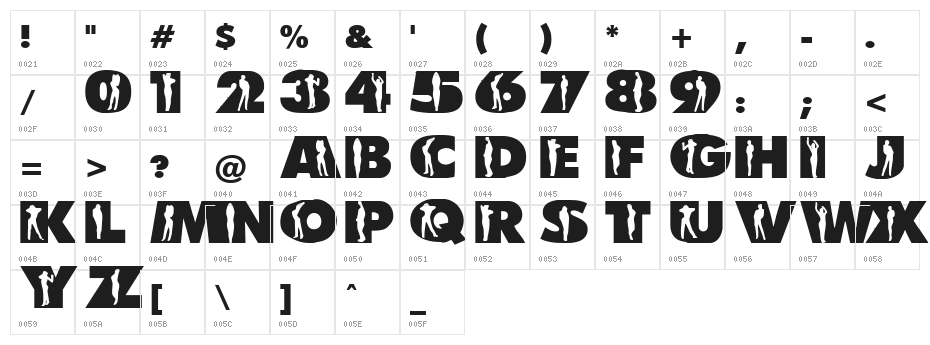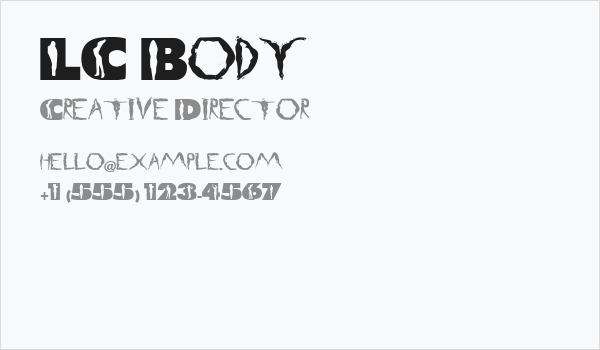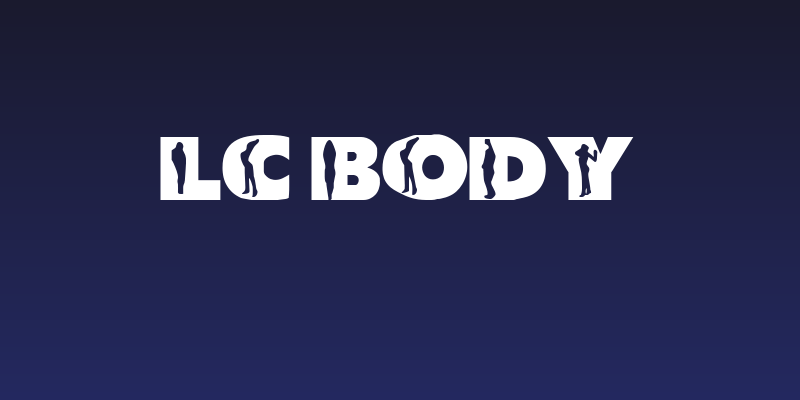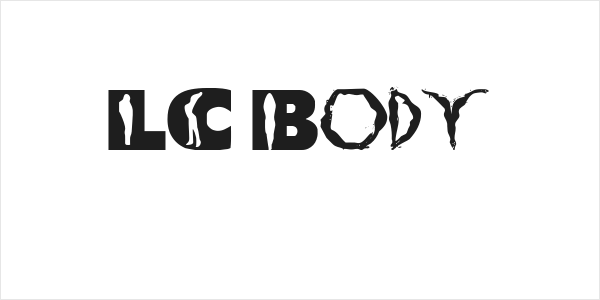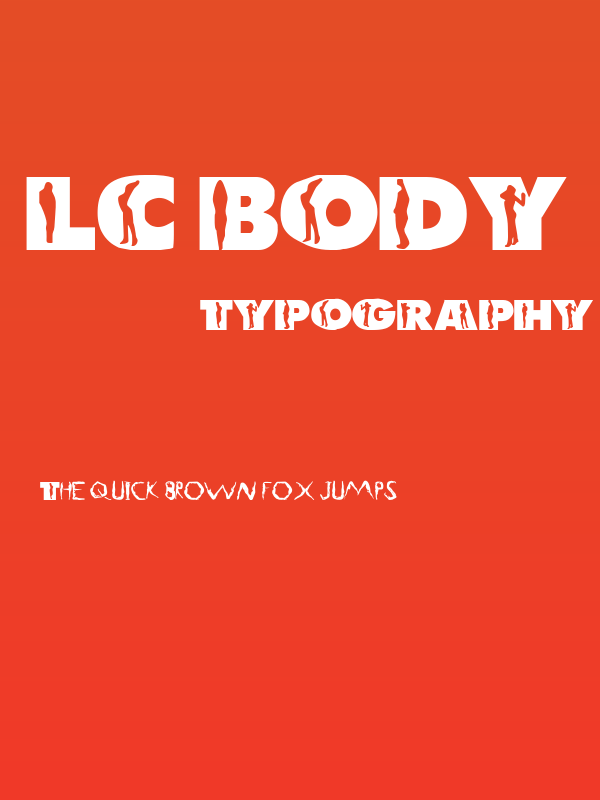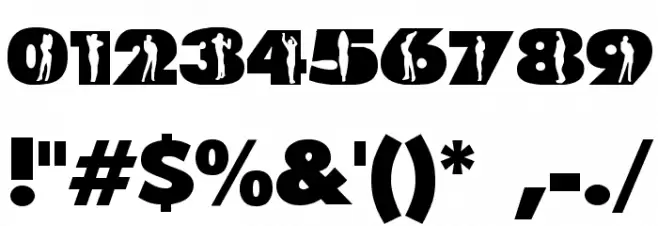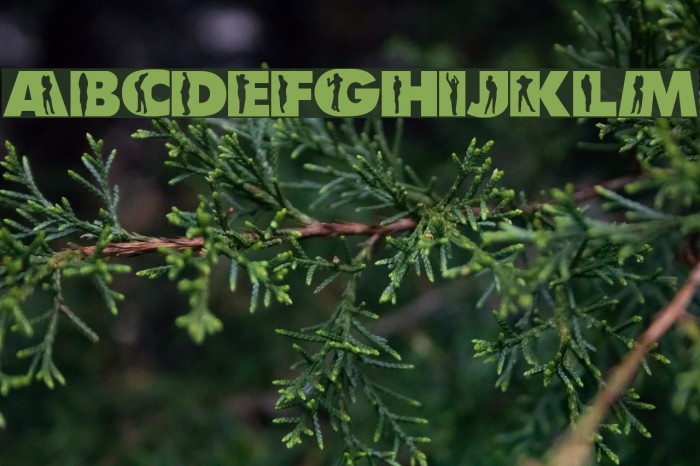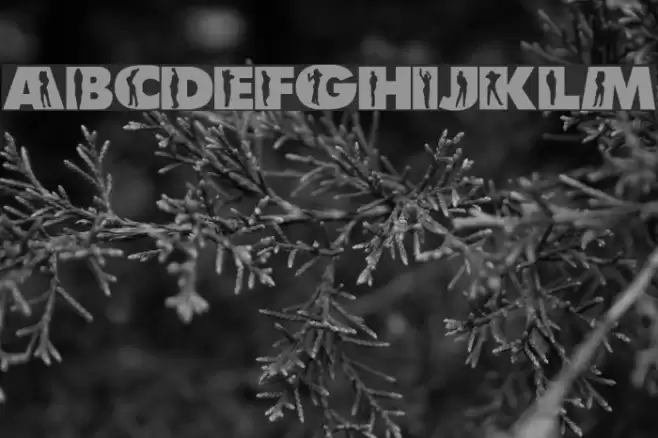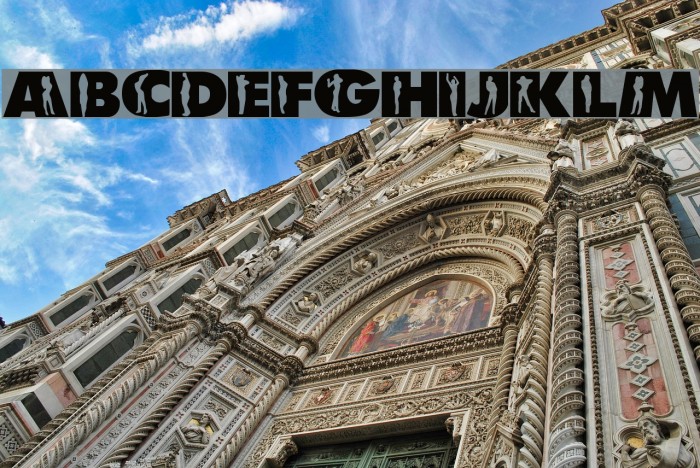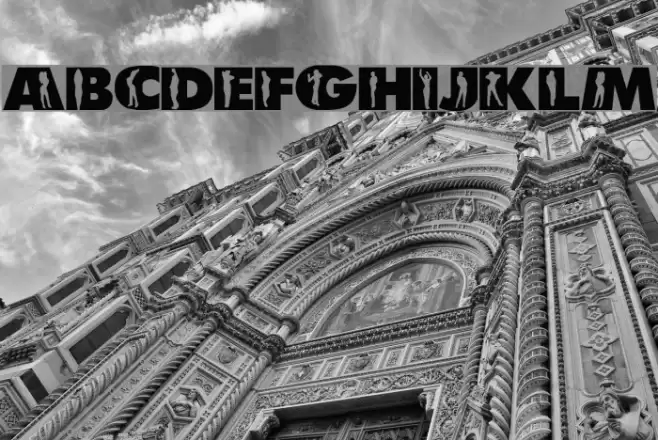
LC Body Font
| Общий стиль | Modern, Artistic |
| Рекомендуемые проекты | Ideal for posters, album covers, branding projects, and any design requiring a bold, artistic touch. |